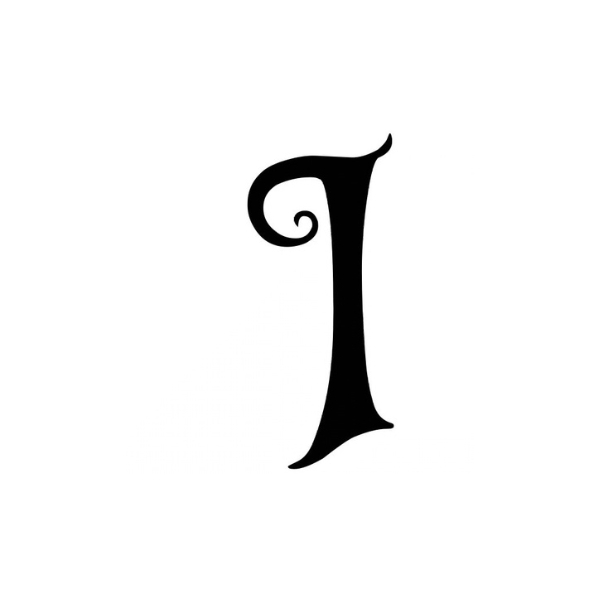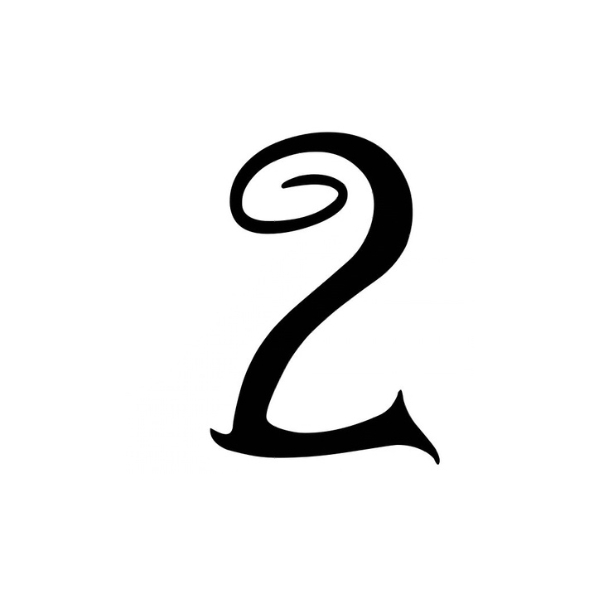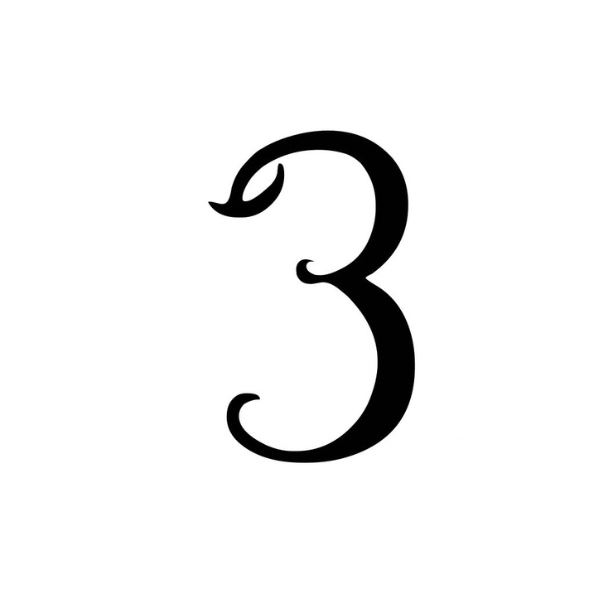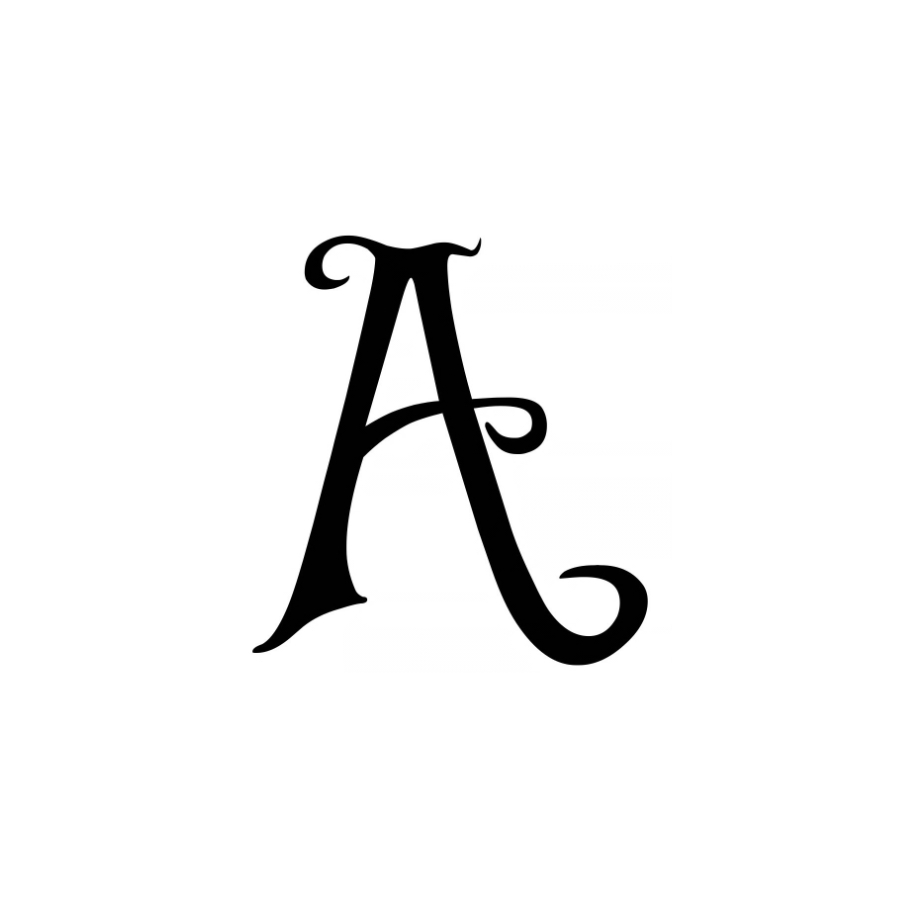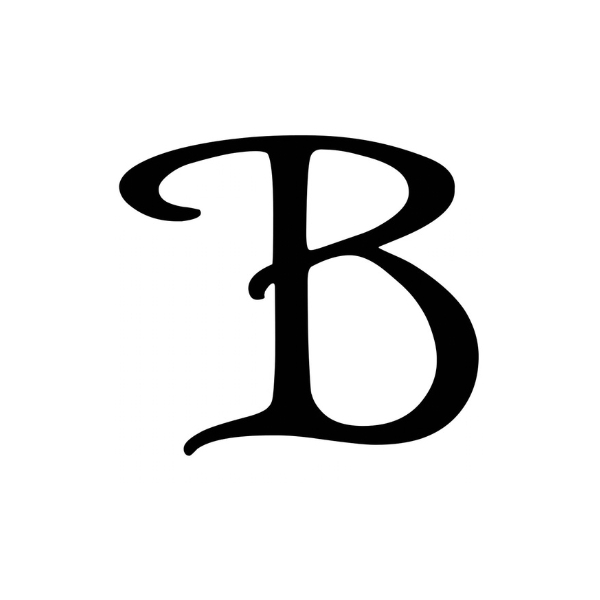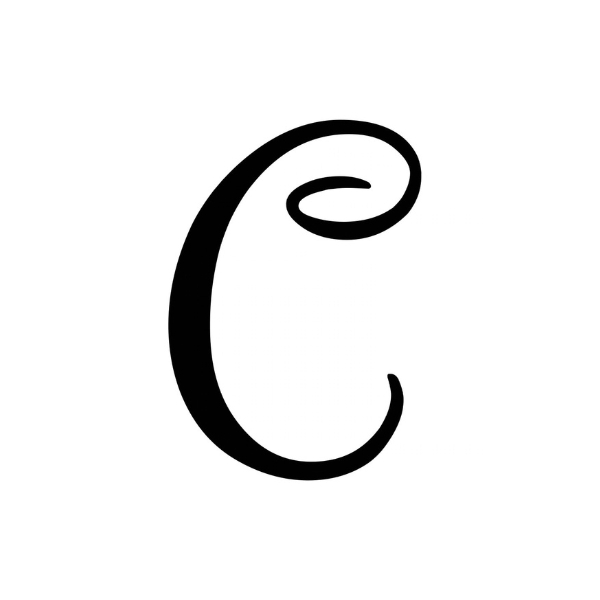
Craft Girl Magic Monogramm Schriftart – Elegantes dekoratives Alphabet | Cricut-kompatibel
• Die Craft Girl Magic Monogramm Schriftart ist eine dekorative Script-Schrift mit eleganten Kurven und verspielten Details. Die Buchstaben besitzen eine leicht fantasievolle Form mit weichen Schwüngen, geschwungenen Linien und künstlerischen Akzenten, die dem Text eine kreative, handgemachte Optik verleihen. Das Gesamtbild wirkt stilvoll und gleichzeitig gut lesbar und eignet sich für viele kreative Gestaltungsprojekte.
• Die Schrift enthält einen vollständigen Zeichensatz mit Grossbuchstaben, Kleinbuchstaben und Zahlen, sodass eine einheitliche Typografie für unterschiedliche Designs möglich ist. Die ausgewogenen Formen und der fliessende Stil sorgen für harmonische Schriftbilder – sowohl bei kurzen Namen als auch bei längeren Texten.
• Diese Monogramm-Schrift eignet sich ideal für Bastelprojekte, personalisierte Geschenke, Etiketten, Wandaufkleber, Grusskarten, Scrapbooking-Layouts, Tassen, Textildesigns sowie dekorative Schriftzüge. Ihr charakteristischer Stil verleiht Projekten Persönlichkeit und eine kreative Note, während die Schrift gleichzeitig klar und gut erkennbar bleibt.